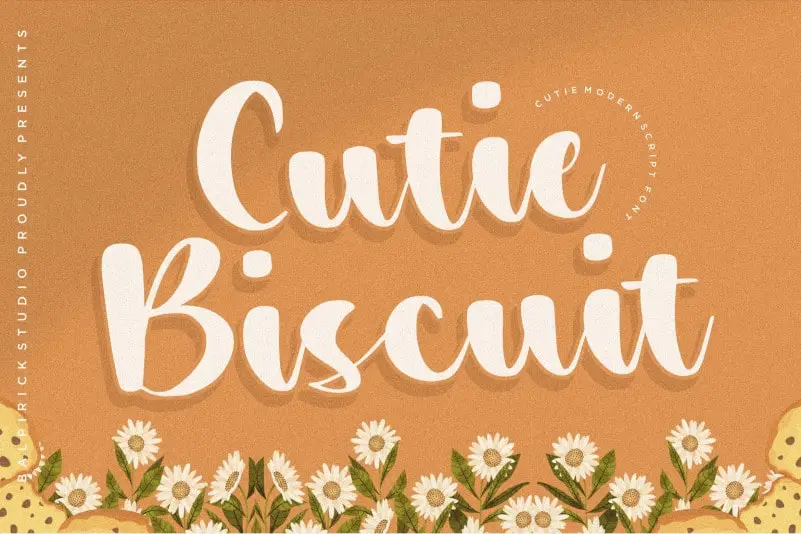
Cutie Biscuit Script Font – Download Grátis
Cutie Biscuit Script Font é uma elegante seleção para criar design visualmente atraente, ideal para um leque amplo de projetos. Seja para aplicar ao seu projeto de embalagem de produto, dar um toque sofisticado à sua identidade corporativa ou mesmo para destacar textos em sua próxima publicação no Instagram, Cutie Biscuit Script traz uma dose especial de delicadeza e charme. O design fluido desta fonte é perfeito para expressar a personalidade de seu projeto acima de um fundo, seja para criar uma sensação de leveza e frescor ou para dar um toque romântico em seus documentos casados. Com Cutie Biscuit Script Font, você está prestes a capturar o coração dos consumidores com elegância e estilo.